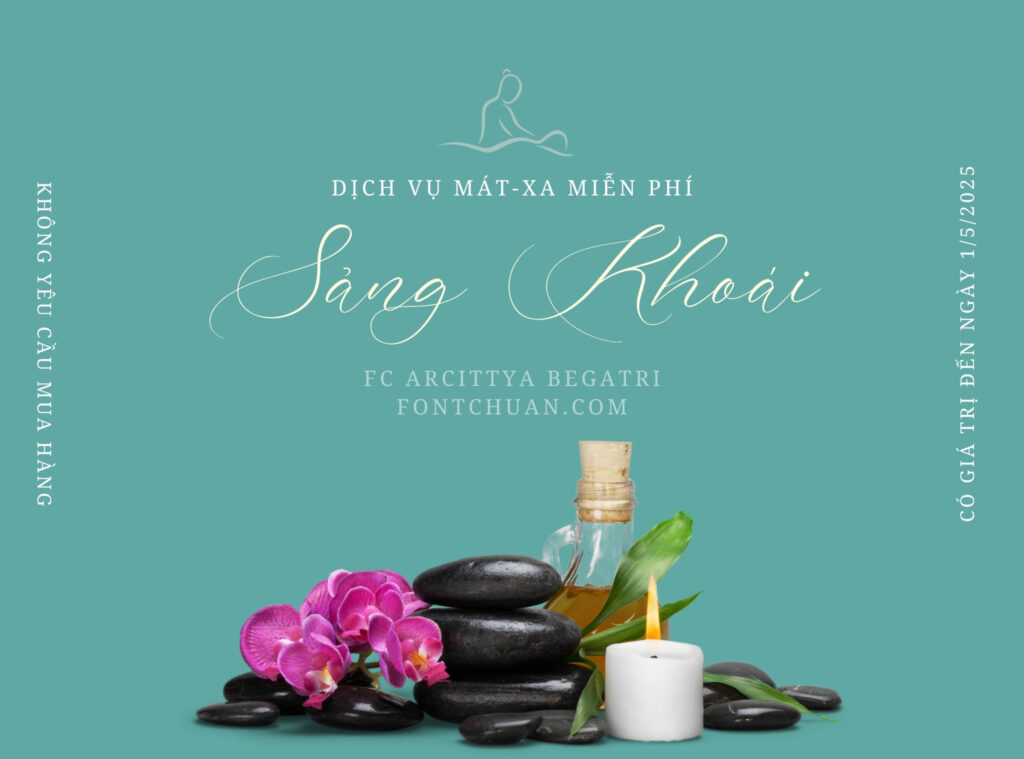
Font FC Arcittya Begatri Việt Hóa
Arcittya Begatri là một font chữ thư pháp đẹp mắt, được thiết kế để nâng cao sự thanh lịch và tinh tế cho các dự án thiết kế của bạn. Với dòng chảy độc đáo và mượt mà, có các ký tự đơn và ghép khá đặc biệt (xem Glyphs), font này không chỉ phù hợp cho các thiết kế sang trọng mà còn có thể được sử dụng như một Font Lễ hội để tạo điểm nhấn vui tươi, ấm áp cho các sự kiện đặc biệt như lễ cưới, ngày lễ tình nhân hay các dịp lễ hội khác.
Để hỗ trợ người dùng tiếng Việt, Font FC Arcittya Begatri Việt Hóa được việt hóa miễn phí bởi Font Chuẩn, đảm bảo hiển thị chính xác các ký tự tiếng Việt. Ngoài ra, Arcittya Begatri còn hỗ trợ tiếng Anh và hơn 40 ngôn ngữ Latin khác, mở rộng khả năng ứng dụng trong các dự án quốc tế.
Với cấu trúc chữ mềm mại, độ dày thanh mảnh và thiết kế tinh tế, Arcittya Begatri phù hợp cho các thiết kế yêu cầu sự thanh lịch và chuyên nghiệp. Đặc biệt, font này thích hợp cho các ngành nghề như thẩm mỹ viện, làm đẹp, thiết kế thiệp cưới, ngày lễ tình nhân, lễ 8/3… và lĩnh vực thời trang, nơi cần sự kết hợp giữa thẩm mỹ cao và chức năng truyền tải thông điệp.